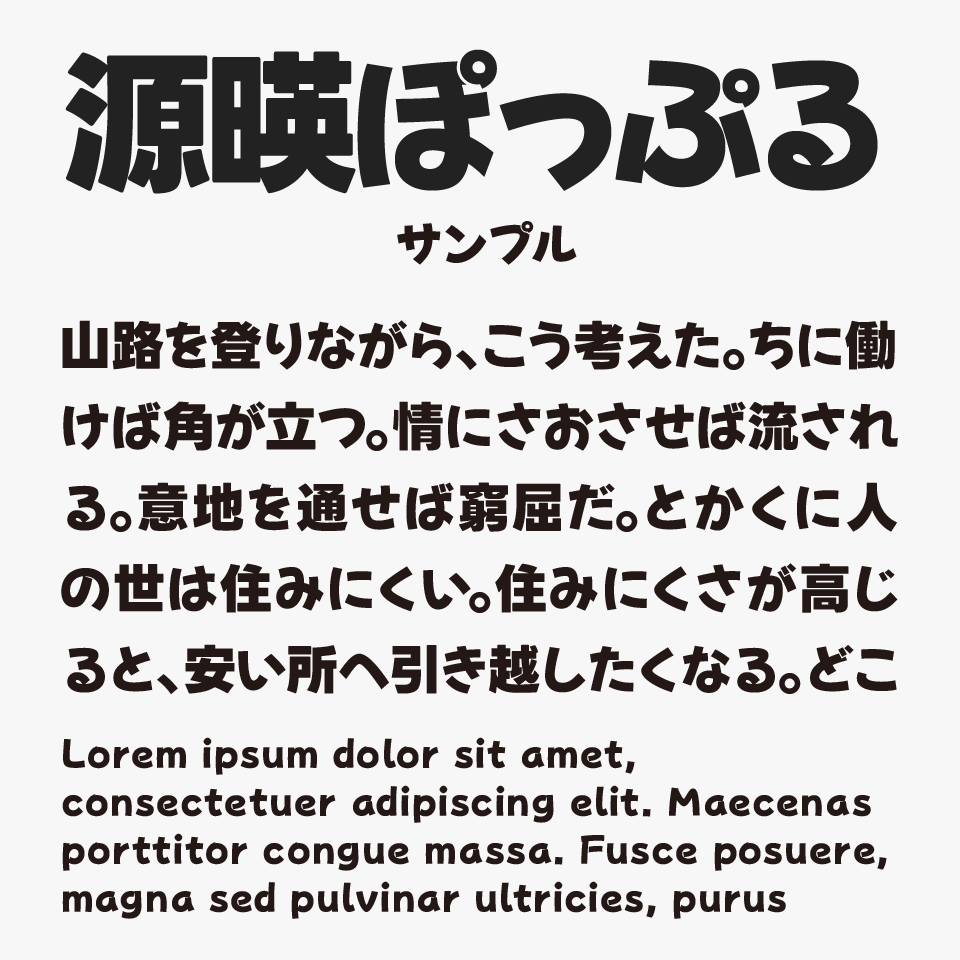
源暎ぽっぷる
源暎ぽっぷるフォントは、手書き風のやわらかな曲線が可愛らしい、ポップ体風かなを取り入れたゴシック体フォントです。
ころころとした丸みのある文字デザインが特徴で、女の子が書いたような親しみやすくポップな雰囲気を感じられます。
また、人気のポップ体フォント「モッチーポップ」から着想を得て制作されているようで、やさしく元気な空気感や、手作り感のある可愛らしさも魅力のひとつです。
タイトル用途はもちろん、動画制作のテロップでも視認性・可読性が高く、さまざまなシーンで幅広く活躍できそうなフォントです。
収録文字は、ひらがな、カタカナ、漢字約7,000文字が収録されています。